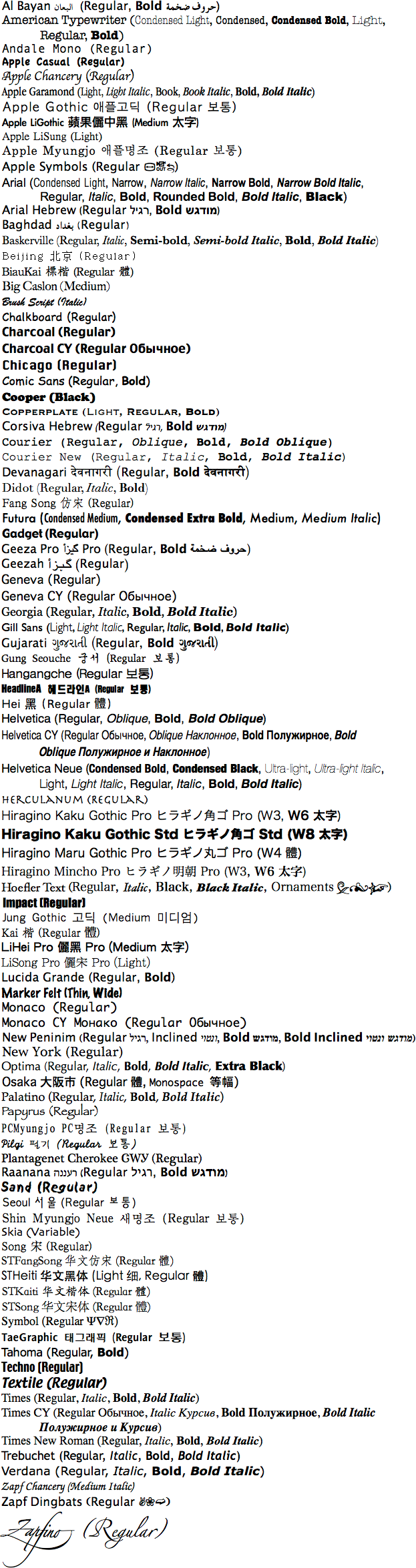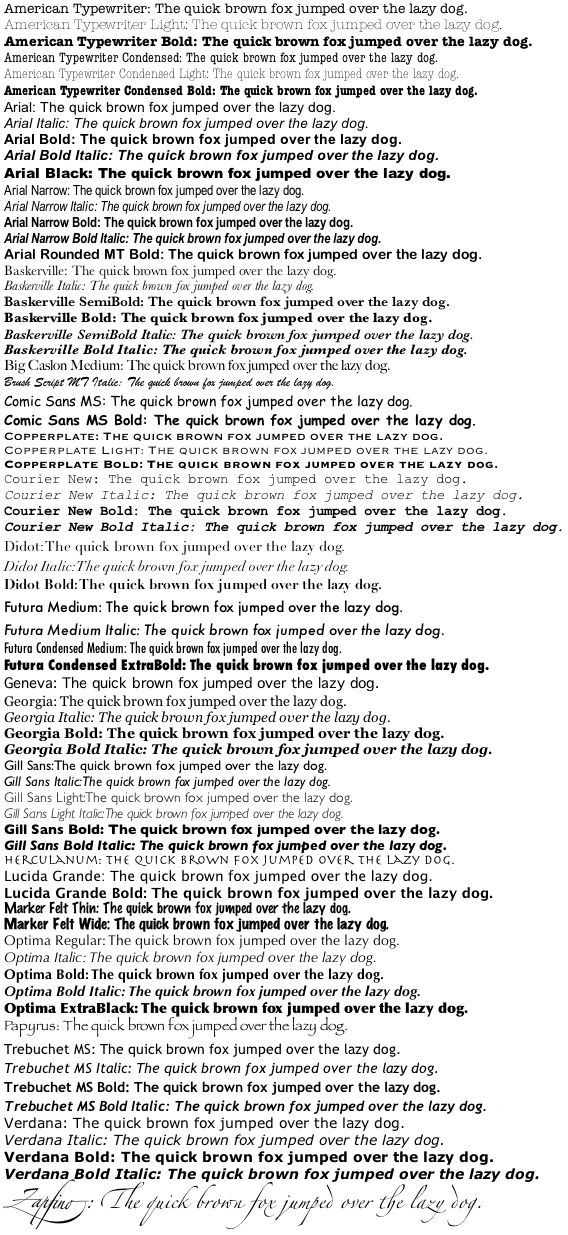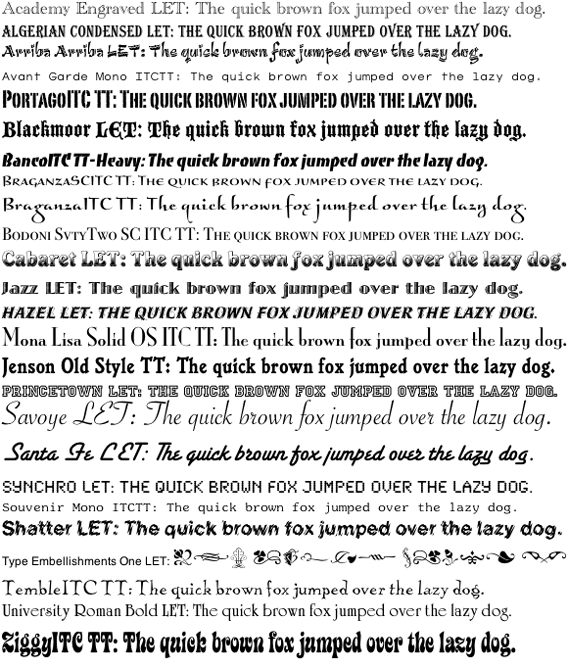
قائمة الخطوط المضمنة في نظام macOS
تحتوي هذه القائمة على جميع الخطوط المُضمّنة مع نظام التشغيل Mac OS X من الإصدار 10.0 إلى الإصدار 10.14 ، بما في ذلك الخطوط التي تم تضمينها مع تحديثات خاصة بلغات معينة من Apple (وخاصةً الخطوط الكورية والصينية). للاطلاع على الخطوط المُضمّنة فقط مع نظام التشغيل Mac OS X 10.5 ، يُرجى مراجعة وثائق Apple .
ملاحظات حول تصنيف الأنواع الفرعية:
- تتمتع بعض الخطوط بتقاليد طباعية ذات تصنيف بسيط نسبيًا يُطابق تصنيف الخطوط الغربية ذات الزوائد/الخطوط المزخرفة. وتُقدم هذه التصنيفات المُطابقة أيضًا. وبشكل أكثر تحديدًا:
- بالنسبة للأبجدية السيريلية واليونانية، يتم التصنيف كما هو الحال في اللاتينية.
- بالنسبة للغات الصينية واليابانية والكورية ، تُصنف الخطوط القوطية لشرق آسيا على أنها خطوط بدون زوائد، وخطوط مينغ/سونغ / باتانغ وفانغسونغ على أنها خطوط ذات زوائد، والأنماط المكتوبة بخط اليد مثل كاي على أنها "خطوط".
- تحتوي الخطوط غير اللاتينية عمومًا على أحرف من الكتابة المقصودة ومجموعة صغيرة من الأحرف اللاتينية. وقد يختلف الجزآن في الأسلوب والتصنيف، ومن هنا جاءت الإشارة إلى "مع جزء لاتيني بدون زوائد".
خطوط النظام حتى نظام التشغيل Mac OS X 10.7
| البيان | غير لاتيني مع سانس لاتيني | عادي، غامق | عربي |
| آلة كاتبة أمريكية | كتاب ذو حروف سميكة مزخرفة | خفيف مكثف، مكثف، مكثف غامق، خفيف، عادي، غامق | |
| أندالي مونو | بدون زوائد، أحادي اللون، كتاب | عادي، غامق | |
| أبل كاجوال | عرض | عادي | مخفي، انظر أدناه |
| محكمة أبل | نص برمجي | عادي | |
| أبل غارموند | كتاب ذو نهايات مزخرفة | خفيف، مائل خفيف، كتاب، مائل كتاب، غامق، مائل غامق | مخفي، انظر أدناه |
| أبل جوثيك | عادي | كوري | |
| أبل ليغوثيك | خطوط غير لاتينية بدون زوائد | واسطة | المطبخ الصيني التقليدي |
| أبل ليسونغ | حروف غير لاتينية ذات نهايات مزخرفة | ضوء | المطبخ الصيني التقليدي |
| أبل ميونغجو | حروف غير لاتينية ذات نهايات مزخرفة | عادي | كوري |
| رموز أبل | صورة | عادي | |
| أكواكانا | عادي | اليابانيون، غير موضحين أدناه | |
| أريال | كتاب بدون زوائد، | خفيف مكثف، ضيق، مائل ضيق، غامق ضيق، مائل غامق ضيق، عادي، مائل، غامق، غامق دائري، مائل غامق، أسود | يأتي مع نظام التشغيل مايكروسوفت ويندوز (باستثناء خط Arial Condensed Light الذي لا يأتي مع نظام التشغيل ويندوز). |
| أريال عبري | غير لاتيني | عادي، غامق | العبرية |
| أيوثايا | غير لاتيني | عادي | تايلاندي ؛ غير موضح أدناه |
| بغداد | غير لاتيني | عادي | عربي |
| سند مصرفي | نص برمجي | عادي | |
| باسكويرفيل | كتاب ذو نهايات مزخرفة | عادي، مائل، شبه عريض، شبه عريض مائل، عريض، عريض مائل | |
| بكين | حروف غير لاتينية ذات نهايات مع حروف لاتينية أحادية النهايات | عادي | الصينية المبسطة ؛ صورة نقطية فقط |
| بياوكاي | نص غير لاتيني مع جزء لاتيني ذو نهايات | عادي | الصينية التقليدية؛ غير موجودة في يوسيميتي وإل كابيتان حتى سييرا. |
| بيج كاسلون | كتاب ذو نهايات مزخرفة | واسطة | |
| برواليا الجديدة | غير لاتيني | عادي، مائل، غامق، غامق مائل | اللغة التايلاندية ، مرفقة مع نظام التشغيل مايكروسوفت ويندوز |
| BrowaliaUPC | غير لاتيني | عادي، مائل، غامق، غامق مائل | اللغة التايلاندية ، مرفقة مع نظام التشغيل مايكروسوفت ويندوز |
| خط الفرشاة | نص برمجي | مائل | |
| كاندارا | كتاب بدون زوائد، | عادي، مائل، غامق، غامق مائل | يأتي مع نظام التشغيل مايكروسوفت ويندوز |
| سبورة طباشيرية | شبه غامق | عادي، غامق | تمت إضافة الخط الغامق في الإصدار 10.4؛ الخط الغامق غير موضح أدناه |
| فرشاة تنظيف بالطباشير | عريض | عادي | تمت إضافته في الإصدار 10.6؛ غير موضح أدناه |
| فحم | عادي | النسخة الكلاسيكية فقط | |
| فحم CY | غير لاتيني | عادي | السيريلية |
| شيكاغو | بدون، كتاب | عادي | النسخة الكلاسيكية فقط، انظر كرونجثيب أدناه |
| كوتشين | كتاب ذو نهايات مزخرفة | عادي، مائل، غامق، غامق مائل | |
| كوميك سانس | غير رسمي | عادي، غامق | يأتي مع نظام التشغيل مايكروسوفت ويندوز |
| كونسولاس | sans-serif, mono | عادي، مائل، غامق، مائل | يأتي مع نظام التشغيل مايكروسوفت ويندوز |
| كوبر | غامق للغاية | أسود | |
| صفيحة نحاسية | serif، عنوان، أحرف صغيرة | خفيف، عادي، غامق | |
| كورسيفا العبرية | غير لاتيني | عادي | العبرية |
| ساعي | خط ذو نهايات مربعة أحادية اللون، كتاب | عادي، مائل، غامق، غامق مائل | |
| صحيفة كوريير نيوز | خط ذو نهايات مربعة أحادية اللون، كتاب | عادي، مائل، غامق، غامق مائل | يأتي مع نظام التشغيل مايكروسوفت ويندوز |
| ديكوتايب ناسخ | غير لاتيني | عادي | خط النسخ العربي ؛ غير موضح أدناه |
| ديفاناغاري | خطوط غير لاتينية بدون زوائد | عادي، غامق | ديفاناغاري |
| ديدو | كتاب ذو نهايات مزخرفة | عادي، مائل، غامق | |
| يوفيميا يو سي إيه إس | كتاب بدون زوائد، | عادي، مائل، غامق | المقاطع الصوتية الكندية ؛ غير موضحة أدناه |
| فوتورا | كتاب بدون زوائد، | متوسط مضغوط، غامق جدًا مضغوط، متوسط، مائل متوسط | |
| أداة | sans-serif, title | عادي | النسخة الكلاسيكية فقط |
| جيزا برو | غير لاتيني مع جزء لاتيني بدون serif | عادي، غامق | عربي |
| جيزة | غير لاتيني مع جزء لاتيني بدون serif | عادي | عربي |
| جنيف | كتاب بدون زوائد، | عادي، غامق | |
| جنيف، قبرص | غير لاتيني | عادي | السيريلية |
| جورجيا | كتاب ذو نهايات مزخرفة | عادي، مائل، غامق، غامق مائل | يأتي مع نظام التشغيل مايكروسوفت ويندوز |